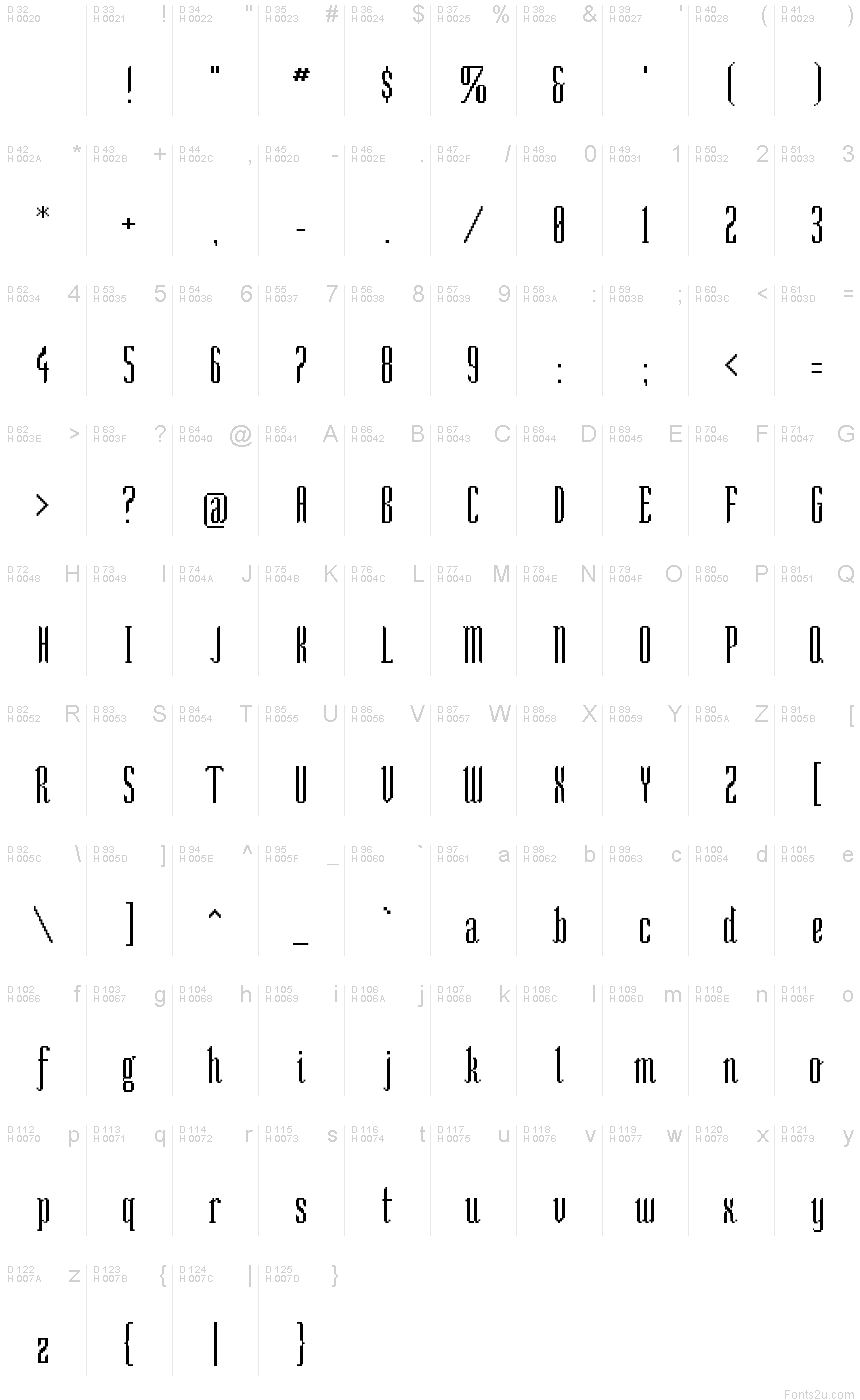
So Narrow od Apostrophic Labs je bitmapové písmo zdarma s vizuálem starých obrazovek. Písmena jsou vysoká a úzká, s výraznými pixelovými schůdky a tenkými mezerami, což jim dodává sevřený, komprimovaný rytmus namísto hladkého geometrického vzhledu.
Hodí se všude tam, kde projekt vyžaduje surovou digitální estetiku: v menu her, na plakátech ve stylu softwaru, webových odznacích, grafikách pro mixtapy a v kompaktních nadpisech. Jako bezplatné písmo je obzvlášť užitečné pro krátký branding, nadpisy s nádechem rozhraní a vrstvené texty, kde úzká konstrukce umožňuje vměstnat více znaků bez ztráty ostrého pixelového charakteru.